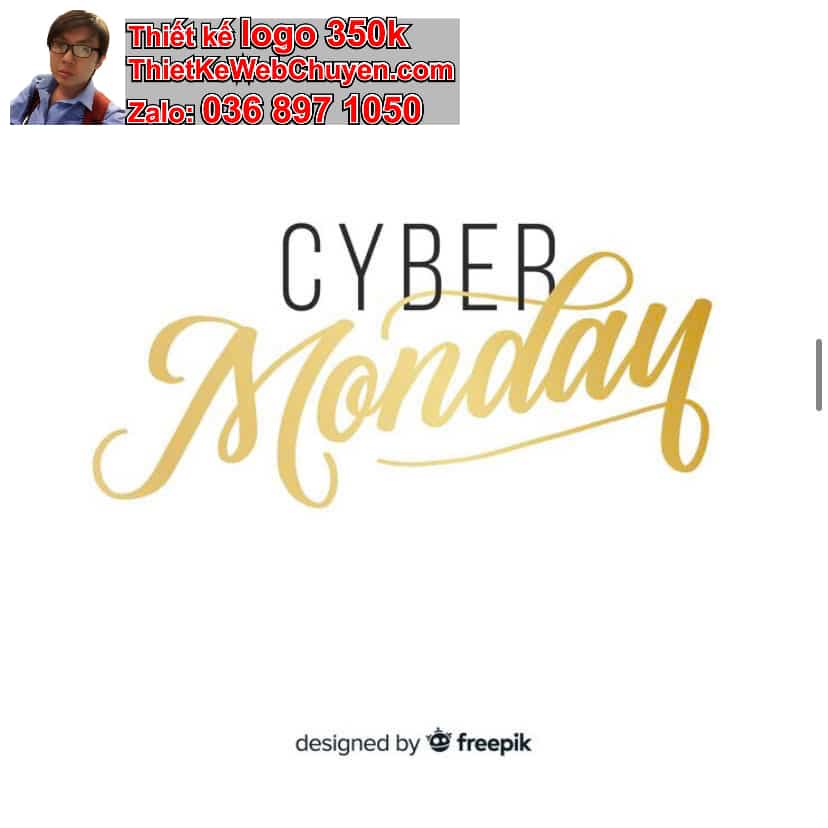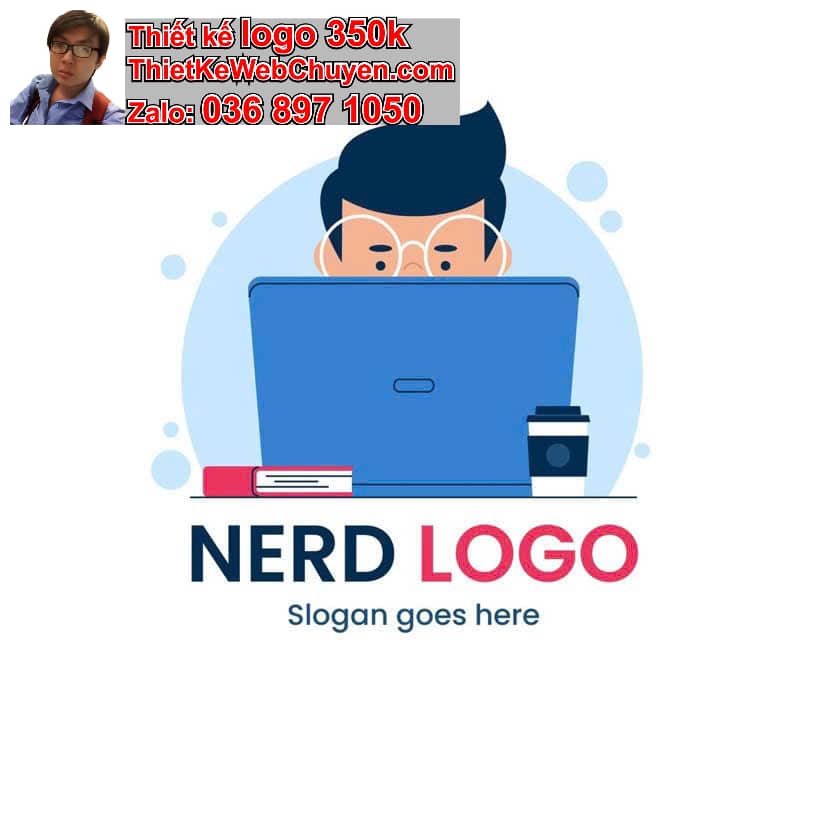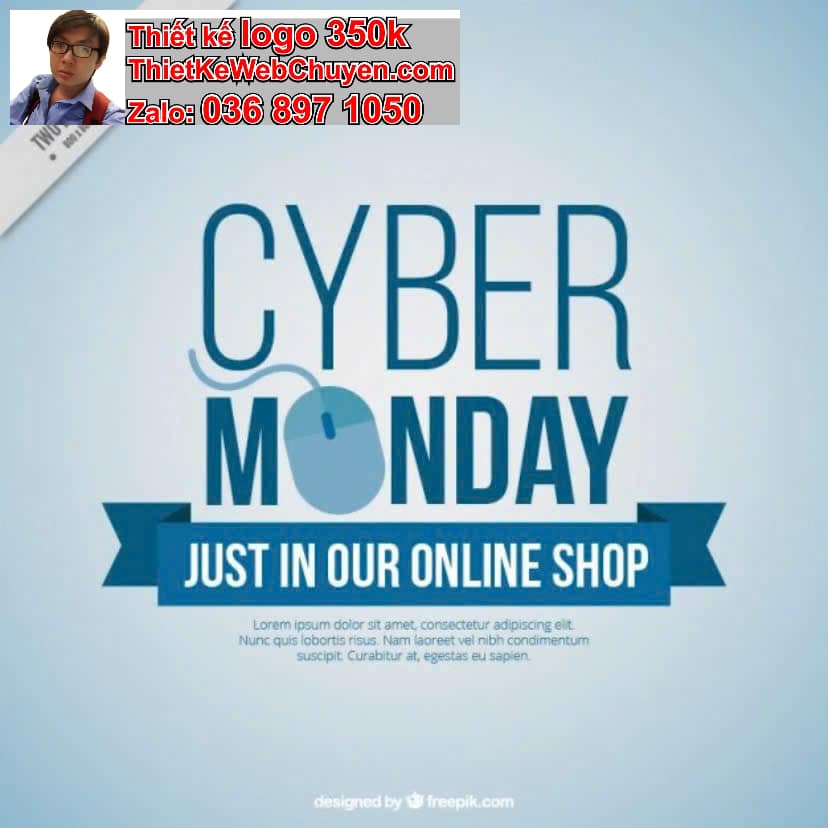
Khi tạo logo online, việc lựa chọn font chữ trong thiết kế logo online đóng vai trò cực kỳ quan trọng, quyết định đến 90% cảm nhận và thông điệp mà thương hiệu muốn truyền tải. Một font chữ phù hợp sẽ giúp logo của bạn nổi bật, dễ nhớ và chuyên nghiệp, trong khi lựa chọn sai có thể khiến thương hiệu mất đi tính nhận diện và sự tin cậy. Bài viết này sẽ cung cấp hướng dẫn toàn diện để bạn có thể tự tin chọn lựa font chữ trong thiết kế logo online hiệu quả nhất.
Tại sao font chữ trong thiết kế logo online quan trọng?
Font chữ không chỉ là yếu tố trang trí mà còn là giọng điệu của thương hiệu. Khi bạn thiết kế logo online, mỗi kiểu chữ mang một cá tính, một câu chuyện riêng, thể hiện giá trị cốt lõi và phong cách của doanh nghiệp. Việc lựa chọn font chữ trong thiết kế logo online đúng đắn giúp:
- Tạo ấn tượng đầu tiên: Logo là bộ mặt của thương hiệu, và font chữ là yếu tố đầu tiên khách hàng nhìn thấy. Ấn tượng mạnh mẽ từ font chữ trong thiết kế logo online sẽ giữ chân khách hàng lâu hơn.
- Truyền tải thông điệp: Một font chữ mạnh mẽ, cổ điển hay hiện đại đều có thể gợi lên những cảm xúc và ý nghĩa khác nhau. Chọn đúng font chữ trong thiết kế logo online giúp truyền tải thông điệp chính xác nhất.
- Nâng cao nhận diện thương hiệu: Font chữ độc đáo và dễ nhận diện giúp thương hiệu của bạn khác biệt so với đối thủ cạnh tranh.
- Đảm bảo tính nhất quán: Sử dụng font chữ nhất quán trên tất cả các kênh truyền thông giúp xây dựng một hình ảnh thương hiệu mạnh mẽ và chuyên nghiệp.
Các nhóm Font chữ trong thiết kế logo online phổ biến khi thiết kế logo online là gì?
Để lựa chọn font chữ trong thiết kế logo online phù hợp, bạn cần nắm rõ các nhóm font cơ bản và đặc điểm của chúng:
1. Font Serif (Chữ có chân)
- Đặc điểm: Có các nét gạch nhỏ (chân) ở cuối mỗi ký tự.
- Cảm nhận: Gợi sự cổ điển, truyền thống, đáng tin cậy, sang trọng, uy tín.
- Ví dụ: Times New Roman, Georgia, Garamond, Lora.
- Phù hợp với: Các ngành nghề truyền thống như luật, tài chính, báo chí, thời trang cao cấp, khách sạn. Đây là lựa chọn tuyệt vời cho các thương hiệu muốn thể hiện sự đẳng cấp và lâu đời khi thiết kế logo online.
2. Font Sans Serif (Chữ không chân)
- Đặc điểm: Không có các nét gạch nhỏ ở cuối ký tự, đường nét đơn giản, hiện đại.
- Cảm nhận: Gợi sự hiện đại, tối giản, thân thiện, rõ ràng, dễ đọc, tiên tiến.
- Ví dụ: Arial, Helvetica, Lato, Open Sans, Montserrat.
- Phù hợp với: Các ngành công nghệ, startup, thiết kế, thời trang trẻ, thương hiệu muốn tạo sự tươi mới, năng động và dễ tiếp cận. Nhiều người khi làm logo online thường ưu tiên Sans Serif vì tính linh hoạt của nó.
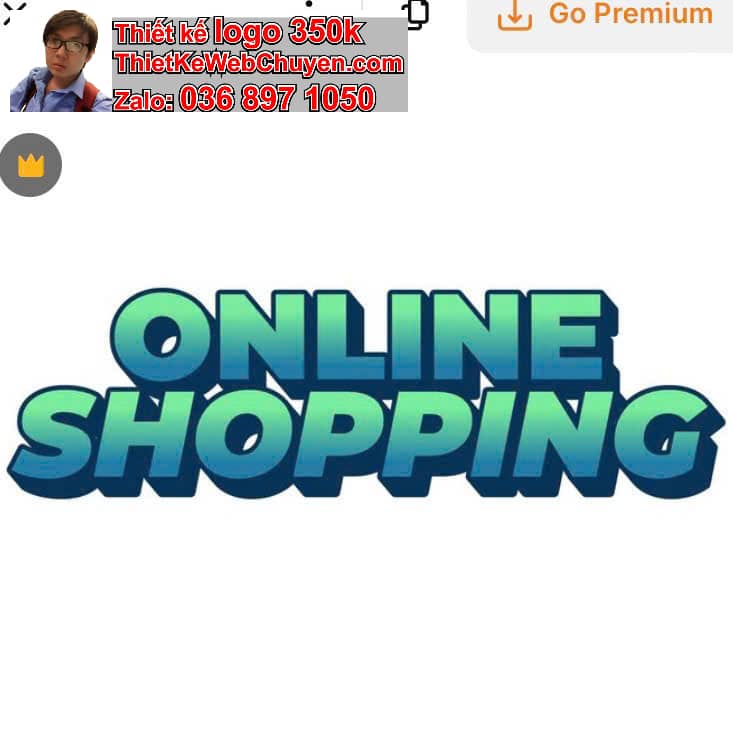
3. Font Script (Chữ viết tay)
- Đặc điểm: Mô phỏng chữ viết tay, có thể mềm mại, uyển chuyển hoặc mạnh mẽ, cá tính.
- Cảm nhận: Gợi sự thanh lịch, cá nhân hóa, sáng tạo, độc đáo, nữ tính (tùy kiểu).
- Ví dụ: Pacifico, Great Vibes, Brush Script MT.
- Phù hợp với: Các thương hiệu thủ công, nghệ thuật, tiệm bánh, studio ảnh cưới, mỹ phẩm. Font Script tạo ra sự khác biệt khi thiết kế logo online và mang lại cảm giác thân mật, gần gũi.
4. Font Display/Decorative (Chữ trang trí)
- Đặc điểm: Có thiết kế độc đáo, phá cách, thường được tạo ra cho các mục đích cụ thể, không dùng cho văn bản dài.
- Cảm nhận: Mạnh mẽ, độc đáo, nổi bật, vui nhộn, cá tính đặc biệt.
- Ví dụ: Impact, Playbill, Lobster.
- Phù hợp với: Tiêu đề, logo, poster, các dự án cần sự nổi bật mạnh mẽ và cá tính riêng. Tuy nhiên, cần thận trọng khi sử dụng nhóm font chữ trong thiết kế logo online này để tránh gây rối mắt.
Làm thế nào để chọn font chữ trong thiết kế logo online phù hợp? (How To)
Việc chọn font chữ trong thiết kế logo online không chỉ là sở thích cá nhân mà còn là một quá trình chiến lược. Dưới đây là các bước và nguyên tắc bạn cần tuân thủ:
1. Nghiên cứu thương hiệu và đối tượng mục tiêu
- Giá trị cốt lõi: Thương hiệu của bạn muốn truyền tải điều gì? (Hiện đại, truyền thống, thân thiện, mạnh mẽ?). Ví dụ, nếu là một công ty công nghệ, font chữ trong thiết kế logo online nên mang hơi hướng hiện đại, tối giản.
- Tính cách thương hiệu: (Vui vẻ, nghiêm túc, sang trọng, năng động?).
- Đối tượng khách hàng: Khách hàng của bạn là ai? Họ mong đợi điều gì từ thương hiệu của bạn? Một font chữ trong thiết kế logo online thân thiện sẽ phù hợp với đối tượng trẻ em, trong khi font Serif có thể thu hút giới doanh nhân.
2. Chọn font chữ chính (Primary Font)
- Đây là font chữ sẽ xuất hiện nổi bật nhất trong logo của bạn.
- Nên chọn một font chữ dễ đọc, độc đáo nhưng không quá cầu kỳ.
- Hãy thử nghiệm các font khác nhau từ các nhóm đã nêu ở trên. Sử dụng các phần mềm thiết kế logo online để xem trước.
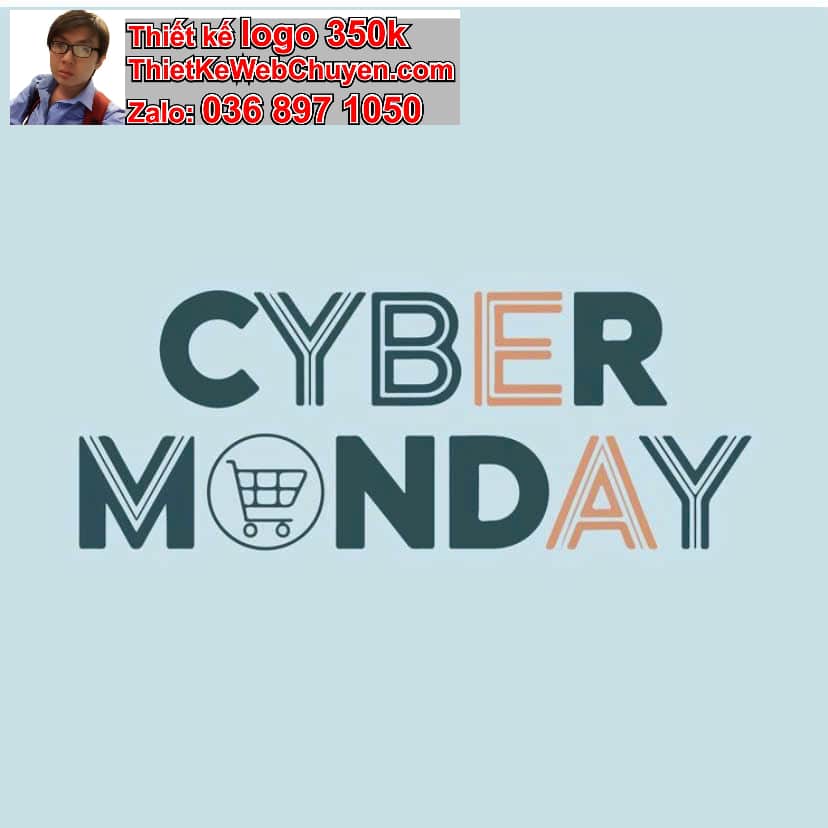
3. Chọn font chữ phụ (Secondary Font – nếu cần)
- Đôi khi, để tạo điểm nhấn hoặc cân bằng, bạn có thể kết hợp hai font chữ.
- Nguyên tắc kết hợp font chữ:
- Tương phản: Kết hợp một font Serif với một font Sans Serif. Ví dụ: font tiêu đề Serif cổ điển, font mô tả Sans Serif hiện đại và dễ đọc.